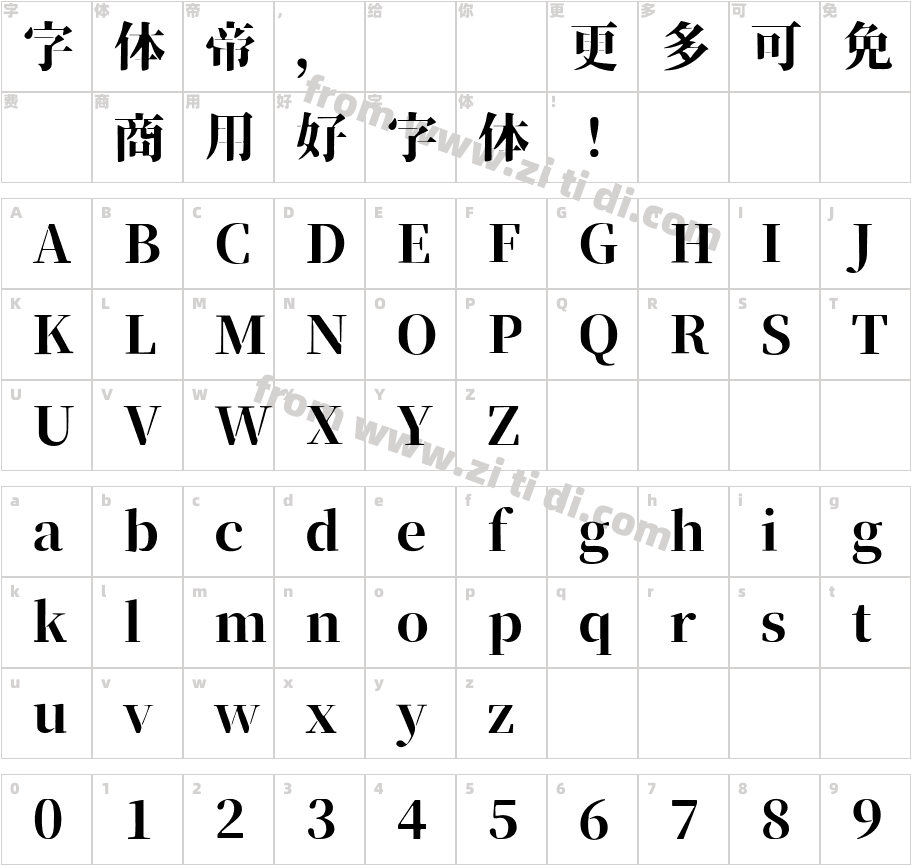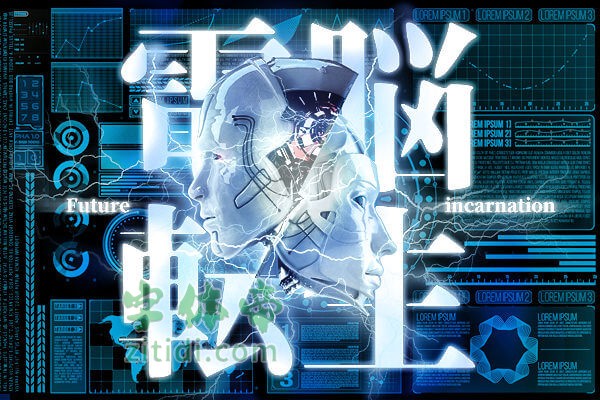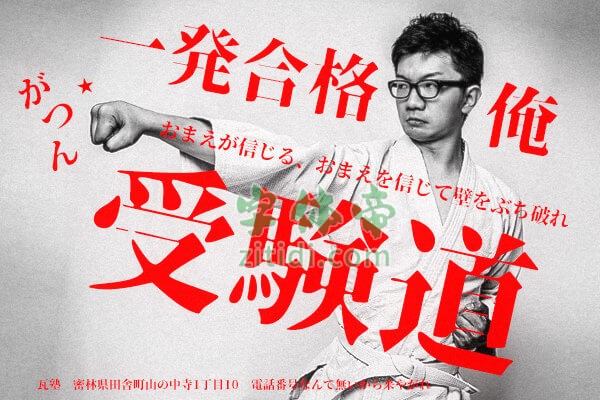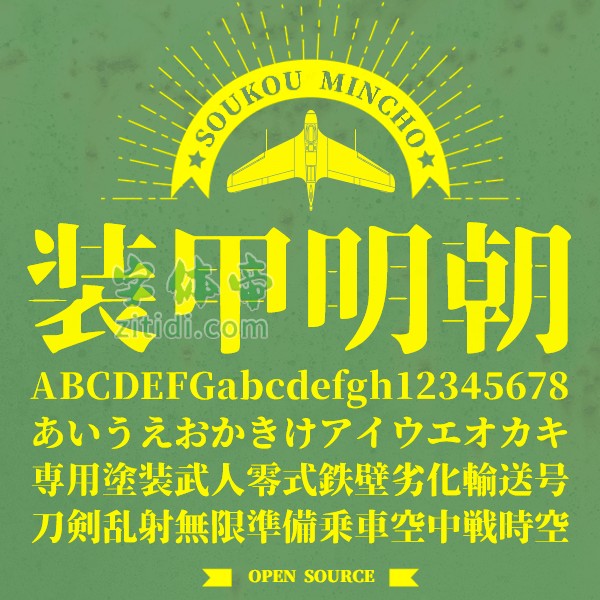
装甲明朝体是一款基于思源宋体修改而成的新字体,可以简单理解成思源宋体的做旧版,出自日本字体爱好者。但因为是日本设计师做的字体,所以对简体中文支持并不是太好,但大多数的常用简体字形还是都有的,如果你发现简体字形在这个字体中无法找到,你可以试试把它转化为繁体字形来试试!
“装甲明朝体”是一款书写很新颖的字体,字体大方,适合各种设计作品使用!欢迎下载!